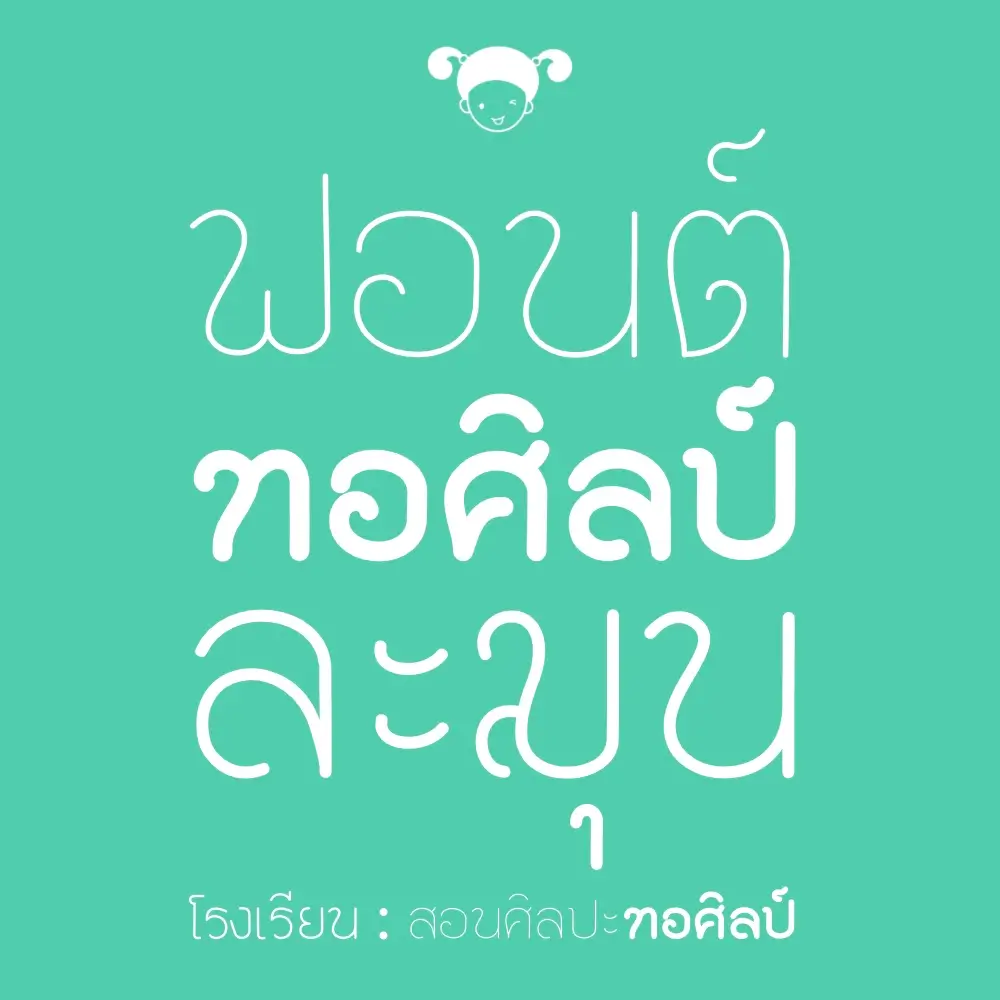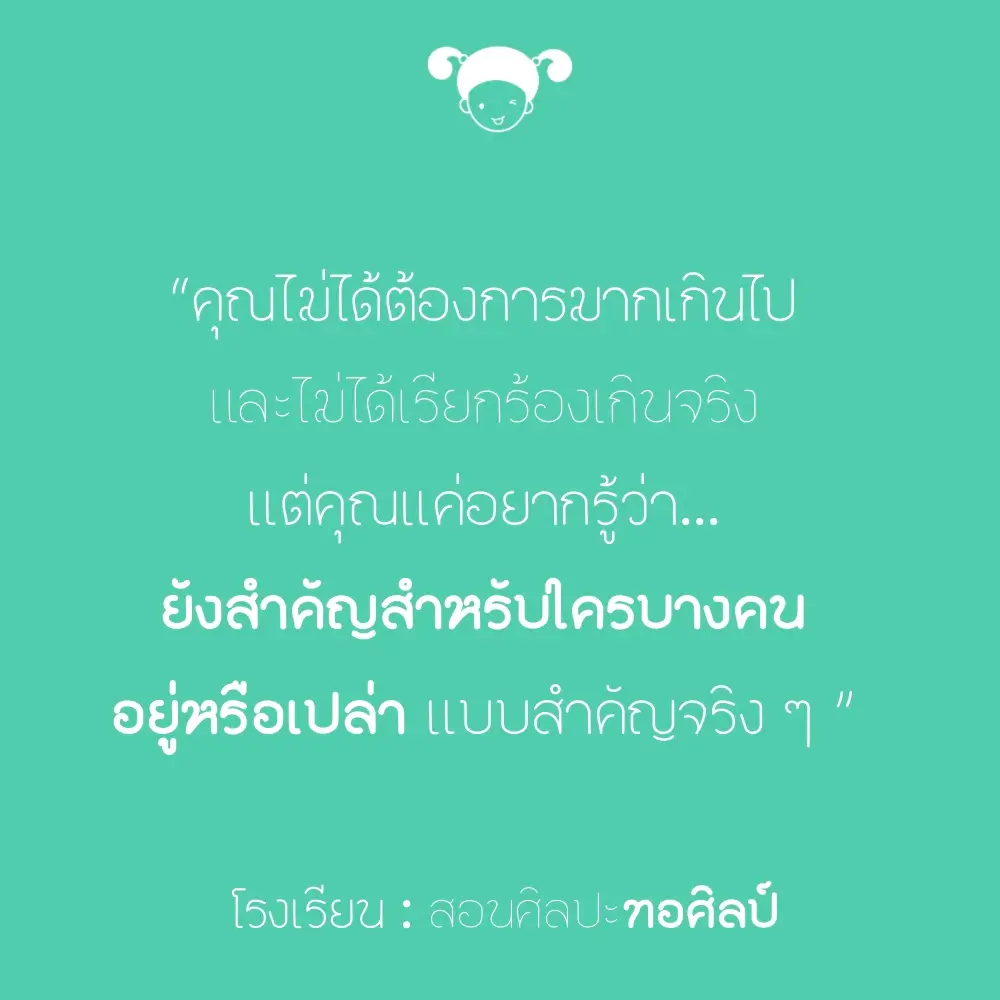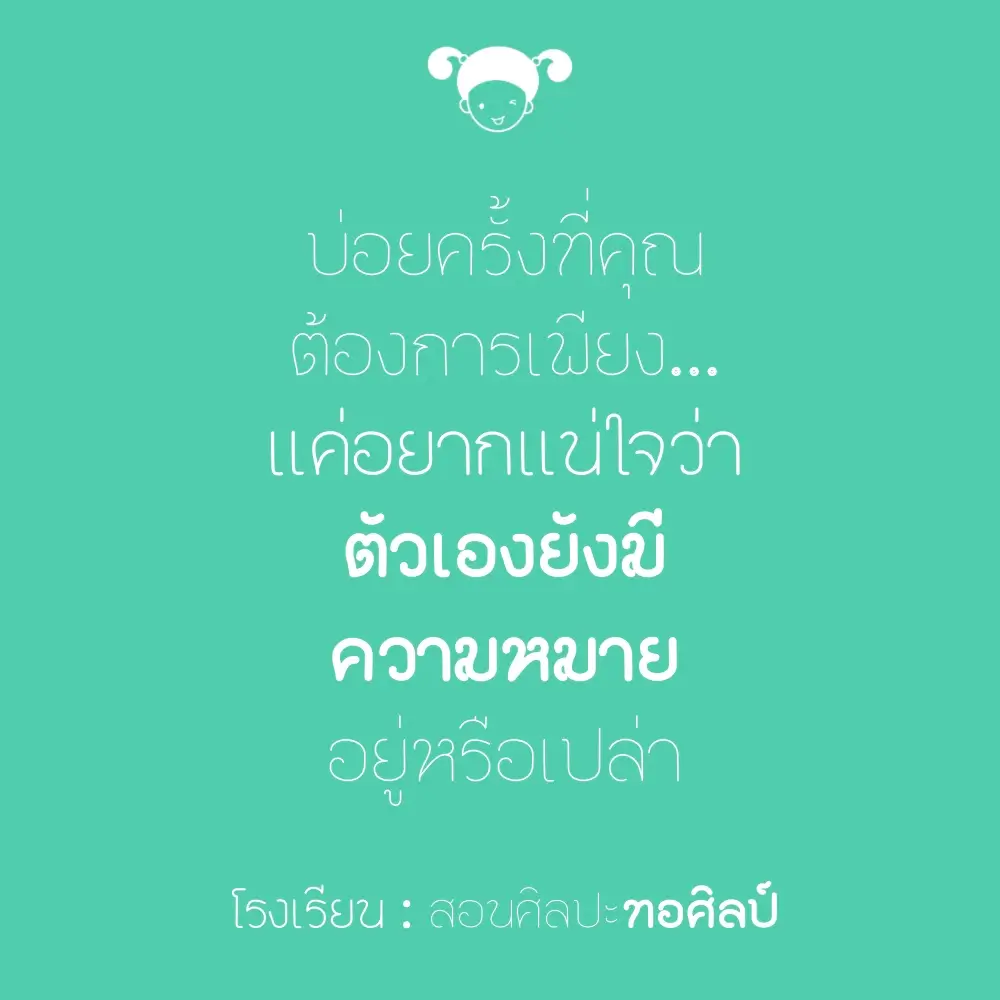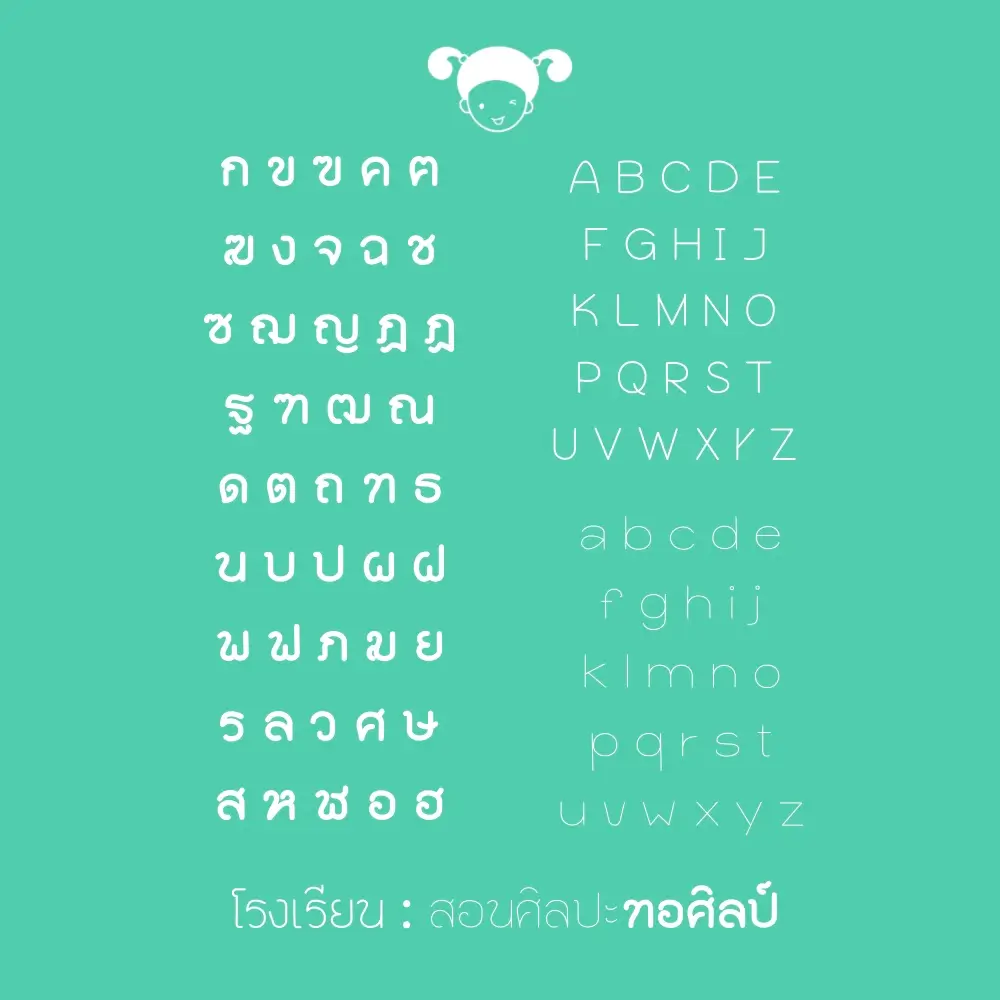
ฟอนต์ “ทอศิลป์ ละมุน” เสร็จแล้ว นุ่มๆ มนๆ และละมุนๆ
มีสามน้ำหนัก (หนา / บาง / บางมาก)
ฟอนต์โดย : ระจัน โรงเรียนสอนศิลปะทอศิลป์
ทอศิลป์ ละมุน (Torsilp Lamun)